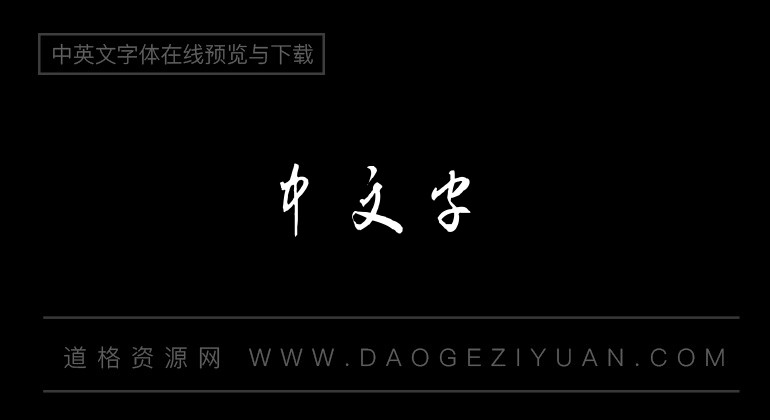
金梅毛草书国际码
金梅毛草书国际码字体是一种基于国际标准Unicode的中文字体,它是一种具有非常优秀的表现力的古典汉字字体,具有清新、活泼、灵动的外形,可以满足多种不同的设计需求。金梅毛草书国际码字体采用了现代技术,拥有良好的放大缩小能力,可以满足不同尺寸的设计需求,使用起来更加顺畅、稳定。
金梅毛草书国际码是一款非常不错的手写艺术字体,具有很好的视觉感,适合于文化类的宣传设计、商业类品牌的广告和产品包装设计以及个性化文字排版等较多场景。